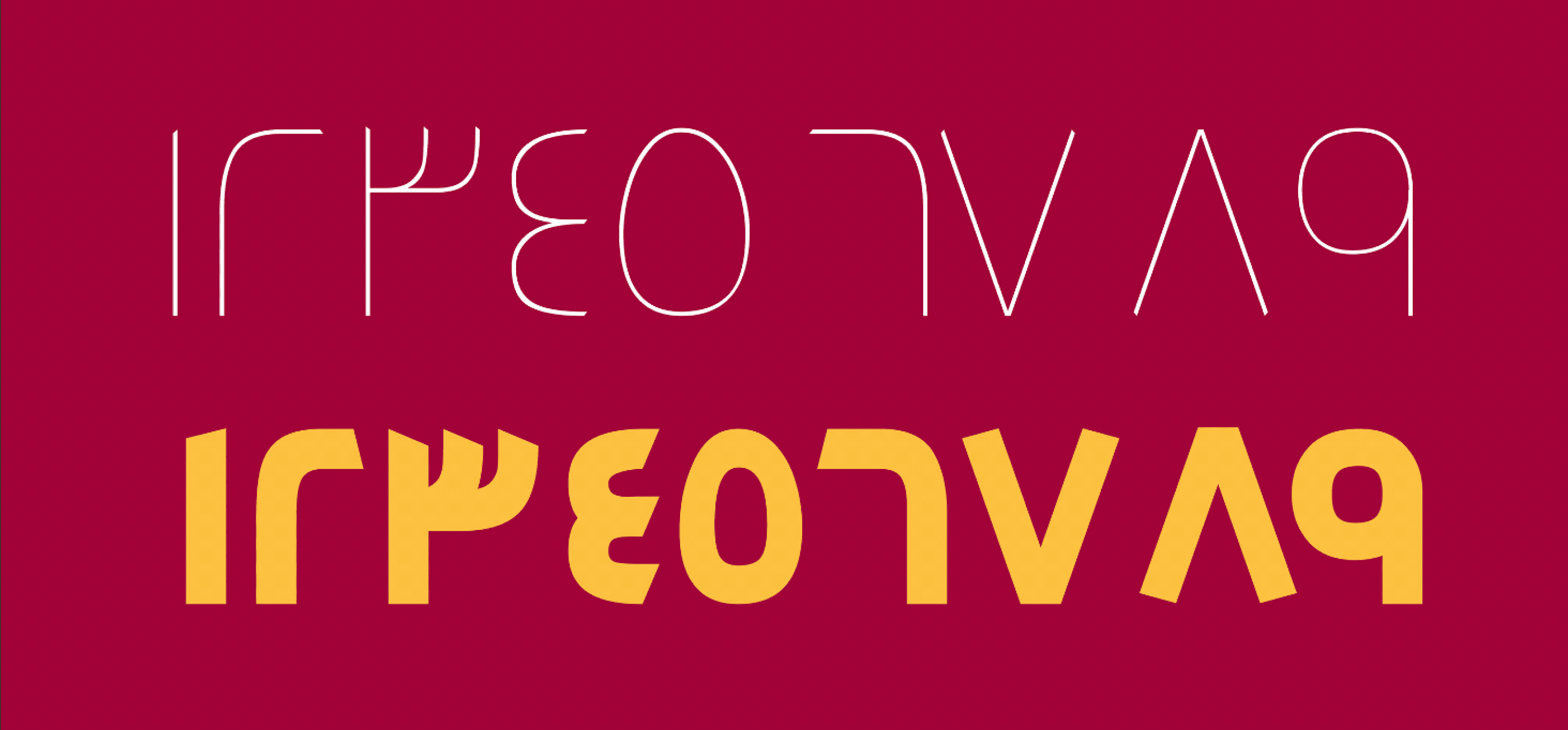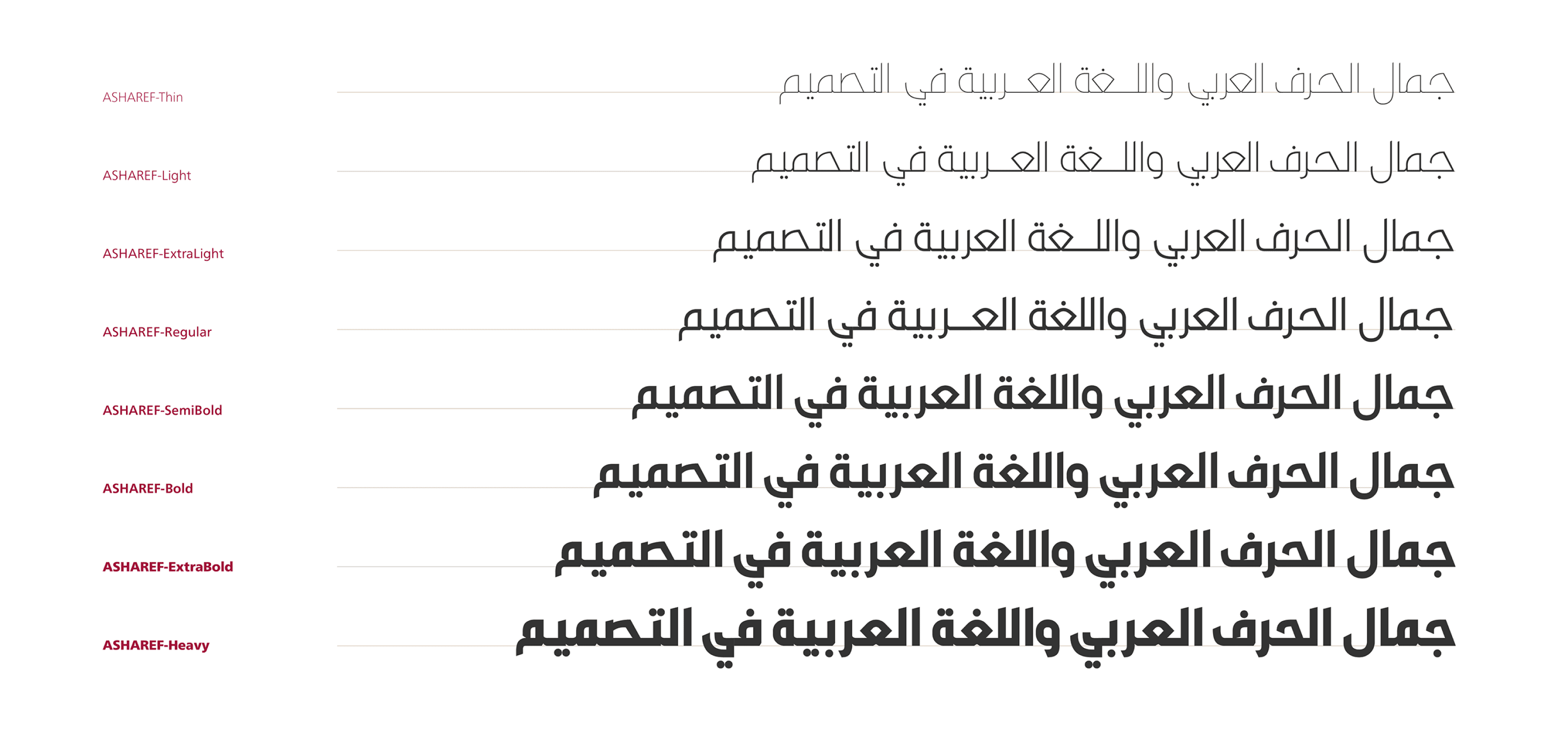
خط عربي هندسي معاصر تم رسمه وبناؤه بعناية، مستوحى من الأسلوب الخطّي التقليدي.
يعتمد تصميم AS HAREF على بنية متوازنة ومنضبطة بصريًا، حيث تتكوّن أشكال الحروف من خطوط رأسية مستقيمة تتكامل بصريًا مع زوايا ناعمة في بعض المواضع.
هذا التوازن بين الصلابة والليونة يمنح الخط طابعًا بصريًا حديثًا يتماشى مع تطورات العصر التقنية والبصرية.
يتوفّر الخط بعدة أوزان وتنوعات، مما يجعله مناسبًا لاستخدام الشركات في أسمائها وهويتها البصرية، بالإضافة إلى العناوين والشعارات. كما يُستخدم بكفاءة في الإعلانات والنصوص الطويلة، سواء في:
العناوين
الشعارات والهويات البصرية
الكتب والمجلات
الموشن جرافيك
الويب والتلفزيون
أس حريف هو خط متعدد الاستخدامات يجمع بين الحداثة والوضوح.